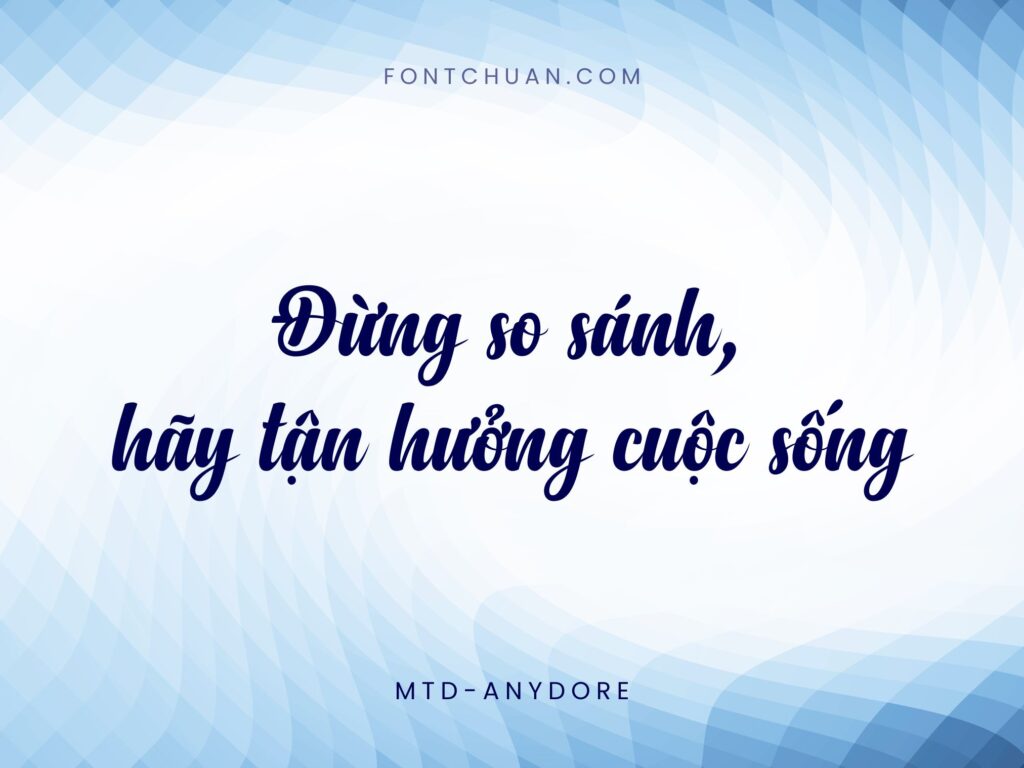
Font Anydore là một kiểu chữ viết tay mạnh mẽ và thanh lịch, được tạo ra bởi nhà thiết kế Situjuh Nazara. Với các nét chữ uyển chuyển và tinh tế, Anydore mang lại cảm giác hiện đại và thu hút cho các thiết kế. Font này đi kèm với nhiều ký tự thay thế, cho phép bạn tạo ra những thiết kế độc đáo mỗi khi sử dụng.
Phiên bản Anydore đã được Việt hóa bởi Mộc Hạ, hỗ trợ đầy đủ tiếng Việt cùng hơn 60 ngôn ngữ khác như Anh, Pháp, Tây Ban Nha, Đức và Ý, mở rộng khả năng ứng dụng trong thiết kế đa ngôn ngữ. Font này đã được thành viên Font Chuẩn sưu tầm và chia sẻ, đáp ứng nhu cầu của cộng đồng thiết kế. Với thiết kế bao gồm các ký tự viết tay mềm mại và đa dạng, Anydore phù hợp cho các ứng dụng như thiết kế logo, thiệp mời, bao bì sản phẩm và các ấn phẩm quảng cáo. Các ngành nghề như quảng cáo, giáo dục, công nghệ và ẩm thực có thể tận dụng font này để tạo ra thiết kế ấn tượng và thu hút.